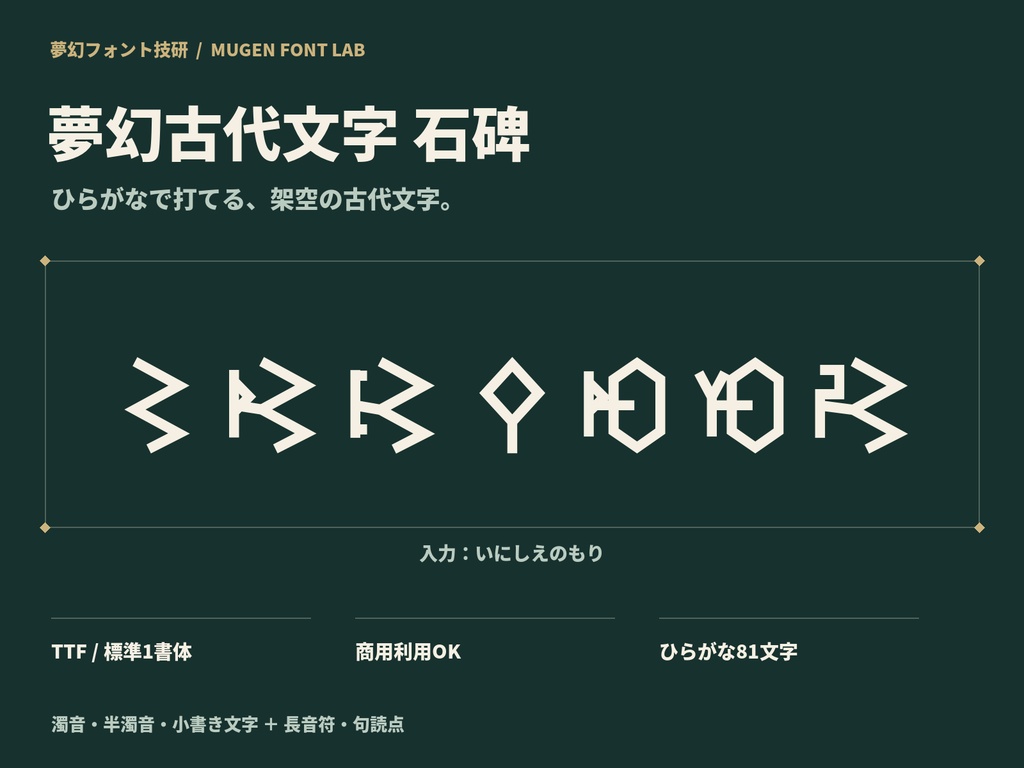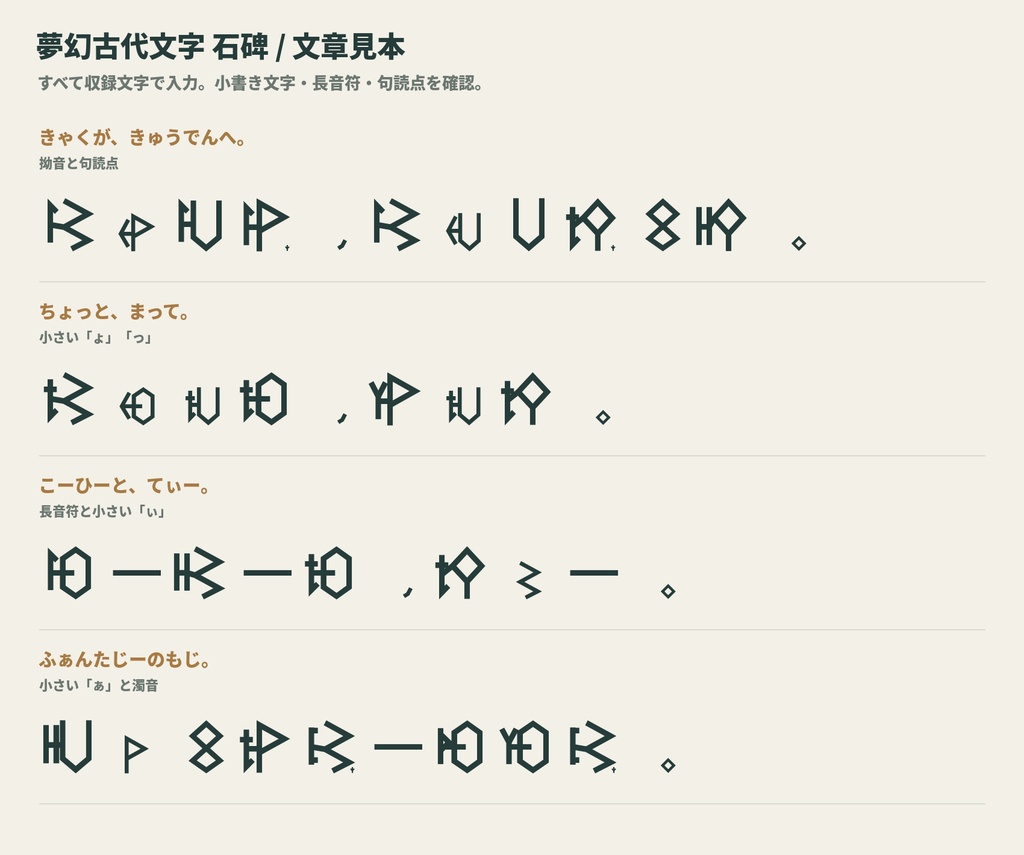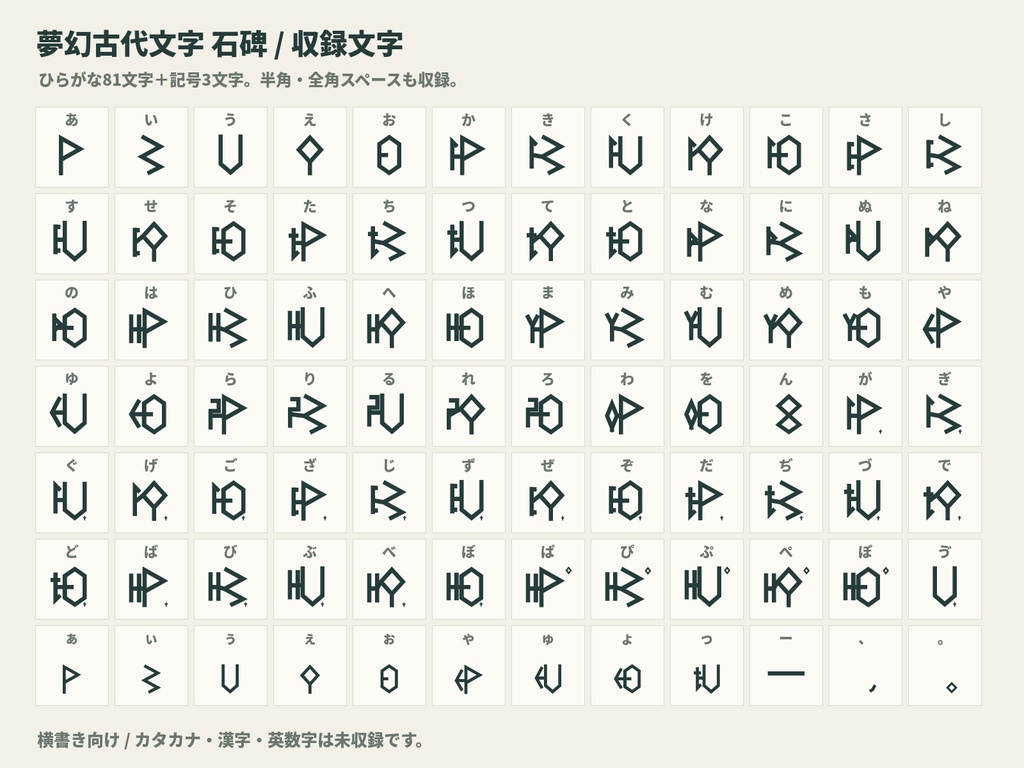
夢幻古代文字 石碑|ひらがなで打てる架空文字フォント
ひらがなを打つと、知らない世界の文字になる。 「夢幻古代文字 石碑」は、石碑や遺跡にありそうな架空文字のフォントです。 ファンタジー作品の看板や地図、古文書、ゲーム・TRPGの資料、動画や配信の画面づくりにどうぞ。 一見読めない文字ですが、母音と行ごとに共通の形があります。対応表を眺めながら、文字を読み解いて遊ぶこともできます。 制作:夢幻フォント技研